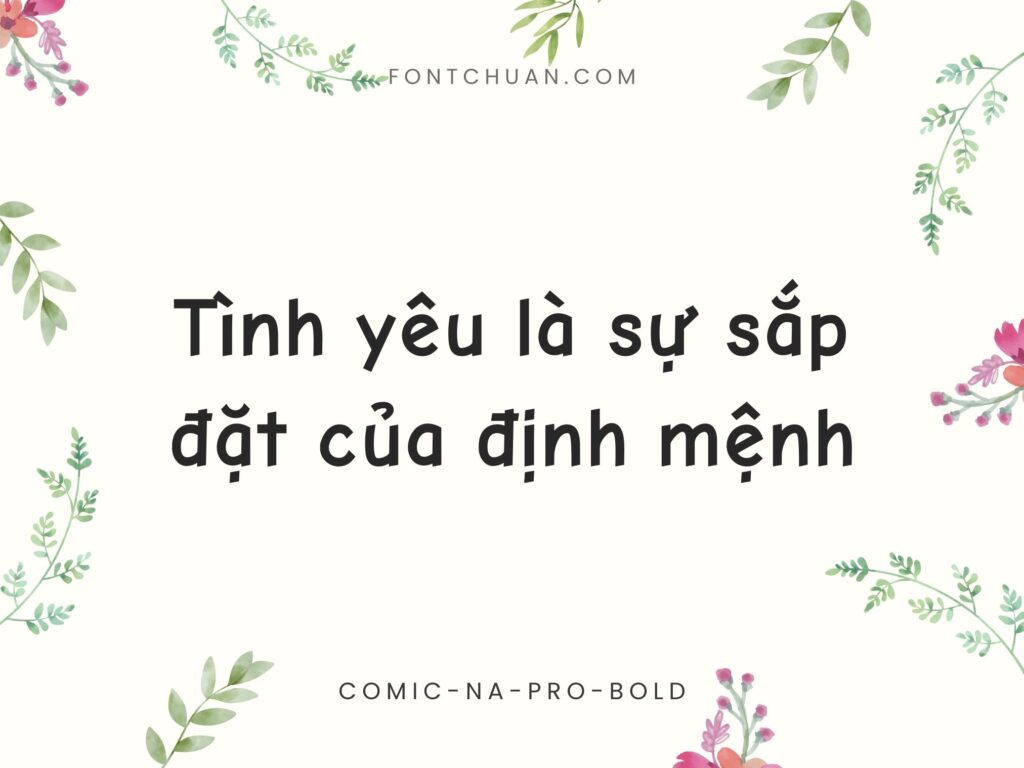
Font Comic Na Pro+ Việt Hóa
Tác giả Font: Craig Rozynski, Hrant Papazian
Comic NA Pro Bold là một font chữ sans-serif được thiết kế với phong cách vui nhộn và thân thiện, lấy cảm hứng từ các kiểu chữ trong truyện tranh. Font này có các đường nét mềm mại và độ dày đồng đều, tạo cảm giác dễ đọc và gần gũi. Comic NA Pro Bold hỗ trợ đầy đủ tiếng Việt và nhiều ngôn ngữ khác, được sưu tầm và đăng bởi thành viên của Font Chuẩn.
Font có thiết kế chữ đậm, tròn trịa và sinh động, phù hợp cho các thiết kế như tiêu đề, poster, truyện tranh, ấn phẩm truyền thông, đồng thời cũng là một Font chữ spa lý tưởng cho các menu dịch vụ, banner, ấn phẩm quảng cáo spa, mang lại cảm giác thư giãn, nhẹ nhàng và thân thiện với khách hàng.